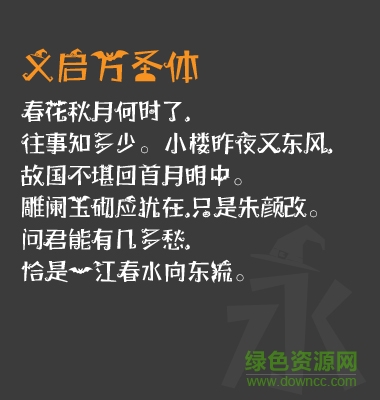
義啟萬圣體字體是一款義啟類萬圣節(jié)專用字體軟件,萬圣體以搞怪搗亂的風(fēng)格給人非常幽默無厘頭的感覺,適合比較有創(chuàng)意的海報廣告標(biāo)題內(nèi)容應(yīng)用,也深受廣大書法家的喜愛,還有更多好看字體盡情期待,歡迎到綠色資源網(wǎng)下載體驗!
魔鬼樹,女巫帽,南瓜燈,吸血蝙蝠,義啟萬圣體陪你過鬼節(jié),快來使用吧,不給糖果就搗蛋?。?!還有豐富的義啟字體,快來綠色資源網(wǎng),說出你想要的字體吧!